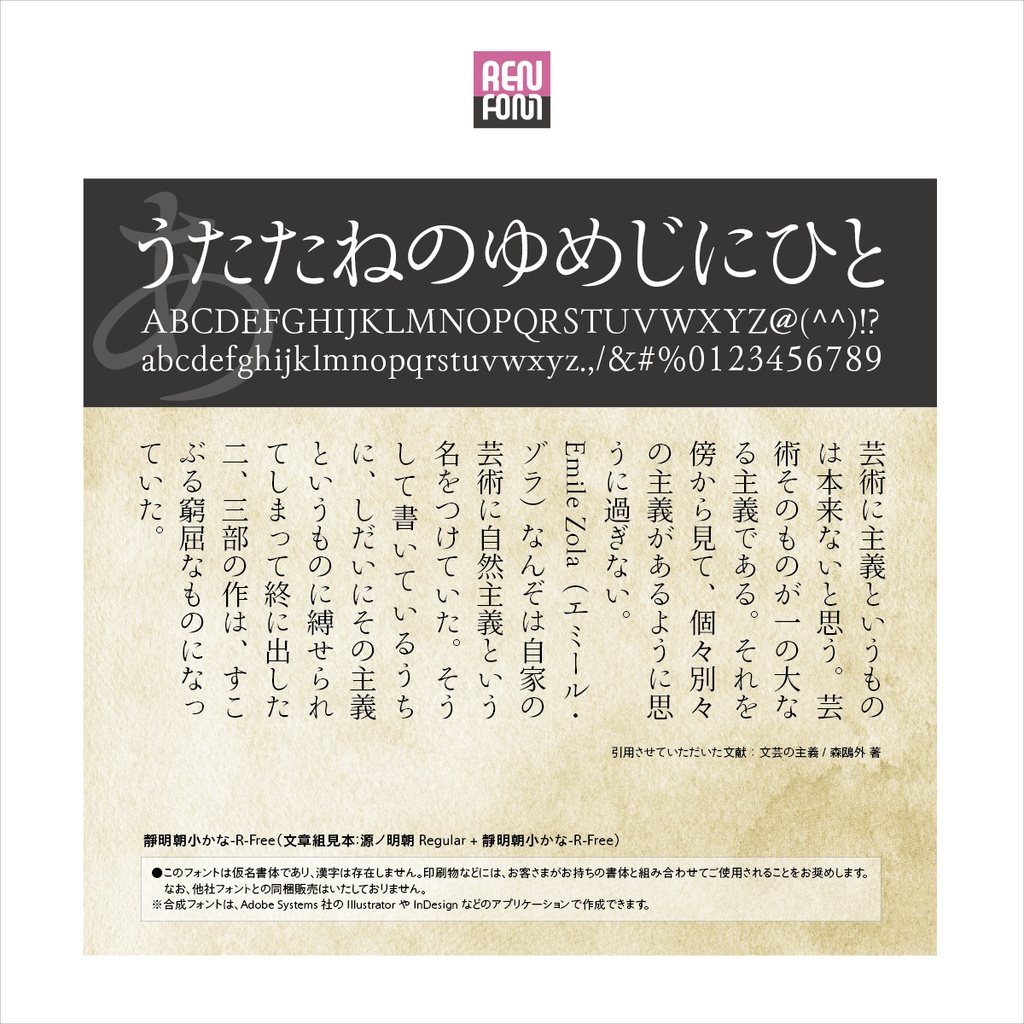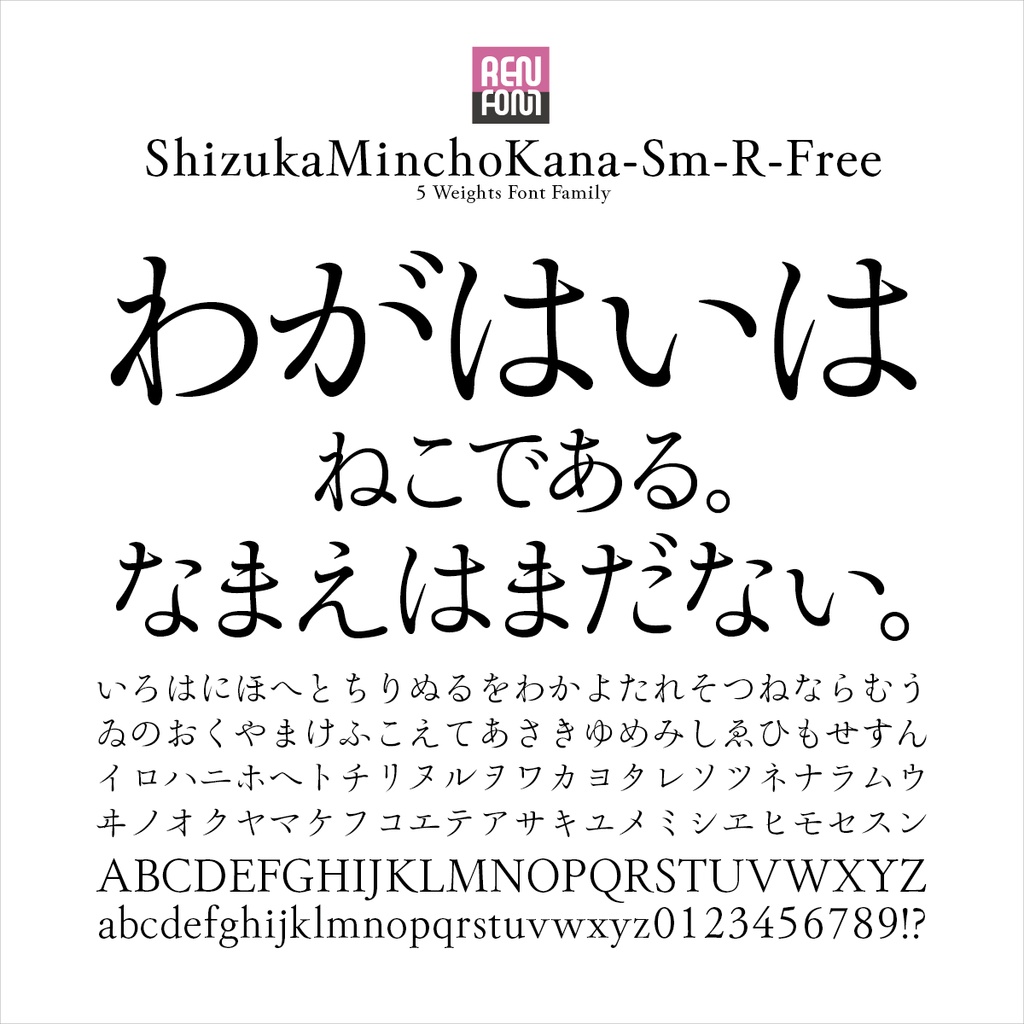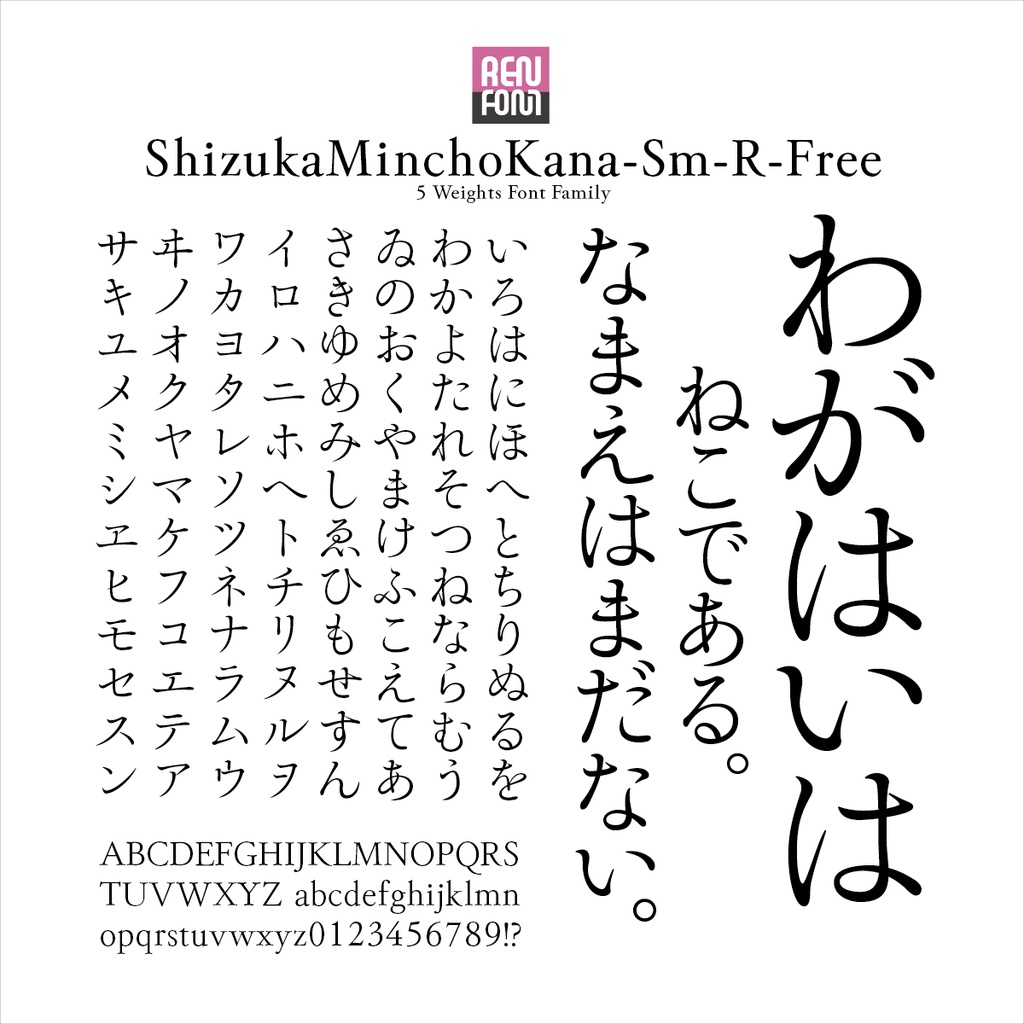
靜明朝小かな-R-Free
味わい深い余韻を残す 靜明朝小かな 5ウェイトファミリー / OpenType
小説などの長文に適した素直なフォルム
伝統書体に似たフォルムをしていますが、復刻版ではありません。現代的な雰囲気も加味した、調和のとれた書体です。明朝体のかな自体もともと独特のクセがあると言えないこともありませんが、靜明朝はそれでも極力「クセ」を抑えた素直な書体となっています。靜明朝には「大かな」と「小かな」があります。このフォントは「小かな」です。縦組みに適しています。純文学にマッチする落ち着いた読みやすい書体です。 この書体は、当社タイプデザイナー金井和夫の普段使いの文字をベースとし、伝統的な明朝体に現代的な雰囲気を加味したフォルムイメージを持っています。「L(ライト)」、「R(レギュラー)」、「M(ミディアム)」、「DB(デミボールド)」、「B(ボールド)」の、合計5ウェイトで構成されています。 また、オールドなイメージを残し、その概念に準じて小仮名に設計しました。それでいながら、近代的な組版にも対応するマルチな性格を備えています。
縦組みに適している理由とは
現代は、すっかり横組みの文化。さすがに新聞はまだ縦組みですが、それ以外では小説などの単行本でしか目にしなくなりました。しかし、かなは本来縦組みに適した作りになっています。それを横組みすると、さまざま問題がおきます。横幅が狭い文字種が多いからです。ベタ組みすると文字間が広く開いてしまう箇所が多くなり、大変読みにくくなります。私たちは実は「習慣」のもとに、普段から読みにくい文章を読まされているのです。 靜明朝小かなは、全体を小さめに設計しました。縦組みには小かなが適しています。一番大きい漢字、ひとまわり小さいひらがな、そして、一番小さなカタカナが混在することにより心地よいリズムが生まれ、読みやすく長時間読んでも疲れないようになっています。
他社「総合書体」との「共存」
現在、世の中に出回っているフォントの数はすでに数え切れないほどになっています。明朝体に限ってもまた然り。 靜明朝かなは5ウェイトありますが、それぞれの太さにさほどの差がありません。本来は3ウェイト展開にすべきかも知れませんが、あえて5ウェイトにしたのにはそれなりの理由があります。 かなフォントは、単独ではあまり存在意義はありません。漢字と組み合わせてはじめて「意味」が生じます。 フォントのウェイト呼称は、ほとんどのベンダが「ライト」から「ウルトラ」に至る7から9ウェイト展開をしています。ただ、それぞれの太さに明確な基準はなく、各ベンダの判断によります。ですので、例えば「ライト」でも太さが微妙に異なってきます。かなフォントがそれに対応するには、細かいウェイト展開が必要となります。 当社かなフォントの細かいウェイト展開は、それが理由です。お好みに合わせて合成フォントをお楽しみいただければ幸いです。